Рукописные русские шрифты с цифрами. Рукописный шрифт для Word
Рукописный шрифт для Word необходим многим людям для написания книги, статей, школьных и других работ. В этой статье мы найдём в Интернете бесплатные рукописные шрифты и на практике установим его в Ворде для дальнейшего использования.
Здравствуйте друзья! В Ворде есть разные шрифты, которые можно использовать во время создания какого-либо материала. Они могут лишь менять вид текста на другие шрифты. Например, можно делать его курсивным и так далее.
Бывают ситуации, когда пользователям нужен уникальный рукописный шрифт для Word. Этот шрифт в тексте отличается от остальных шрифтов тем, что он имеет вид рукописи. Как будто его написал от руки человек. Зачем он вообще нужен, если можно писать любые документы в Ворде со стандартным шрифтом?
Иногда возникает такая необходимость. Например, в школьных заведениях или в Институтах задают домашние задания, которые нужно выполнить написав их от руки.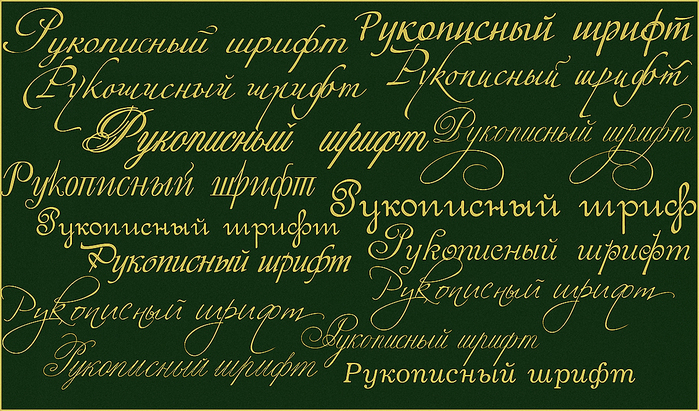
Эту проблему можно решить, если использовать бесплатные рукописные шрифты. Об этом, мы поговорим подробно.
Теперь, мы сделаем тетрадный лист. Нажимаем на вкладку «Вид» наверху панели управления Ворда (Скрин 4).
И устанавливаем галочку напротив функции «Сетка». После этого у Вас будет виден лист A4 в виде тетради.
Если Вы будете распечатывать такой документ через принтер, тетрадный лист может не сохраниться во время распечатки.
Чтобы этого не допустить, заходите в раздел «Вставка», «Фигуры» (Скрин 5).
И прямой линией обводим всю таблицу — по горизонтали, и вертикали. После этого документ можно сохранить в виде тетрадного листа.
А теперь, мы перейдём к процессу написания этого шрифта самым лёгким способом. Открываем документ Ворд и сначала из наш «Denistiana» (Скрин 6).
Пишем какое-нибудь предложение, чтобы увидеть результат созданного рукописного текста (Скрин 7).
Всё работает быстро, и без каких-либо программ можно создать любой рукописный шрифт.
ЗаключениеВ статье мы рассмотрели вопрос, рукописный текст для Word. Были рассмотрены лучшие способы установки такого шрифта. Есть вариант, которой поможет Вам использовать уже готовые шрифты в Ворде. Они встроены в этот текстовый документ и их не нужно искать в Интернете. Думаю, эта статья поможет Вам в создании и написании рукописного текста. Удачи Вам!
При составлении и написании любого текста необходимо уделять внимание его оформлению, а именно шрифтам. Не забывайте о том, что главная цель любого текста — донести до аудитории вашу идею, однако внешний вид также помогает и способствует этому.